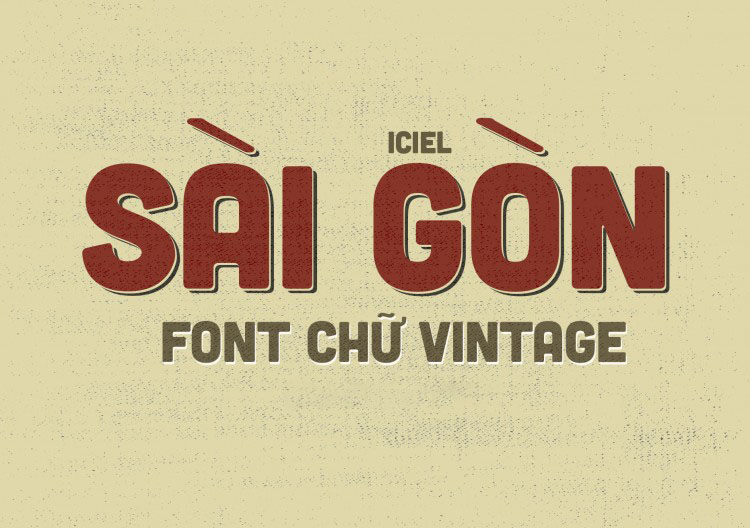
Font chữ béo (Extra Bold hoặc Black) là các kiểu chữ có độ dày nét lớn, mang lại hiệu ứng thị giác mạnh mẽ và khả năng thu hút sự chú ý ngay lập tức. Việc sở hữu bộ download font chữ béo giúp các nhà thiết kế và kiến trúc sư tạo ra những tiêu đề nổi bật cho hồ sơ dự án, bảng hiệu homestay hay các ấn phẩm truyền thông thương hiệu.
Đặc điểm nhận diện của dòng font chữ béo trong thiết kế đồ họa
Điểm lôi cuốn của các bộ phông chữ này chính là cấu trúc nét dày, vững chãi, tạo nên sự tin cậy và trọng lượng cho thông điệp. Khác với các kiểu chữ mảnh mai thanh thoát, font chữ béo tập trung vào việc chiếm lĩnh không gian hiển thị, giúp các từ khóa quan trọng trở nên tách bạch hoàn toàn với phần nội dung phụ. Các phiên bản Việt hóa được tinh chỉnh kỹ lưỡng giúp các dấu thanh (huyền, sắc, hỏi, ngã, nặng) không bị bết dính vào thân chữ, duy trì sự mạch lạc và tính thẩm mỹ ổn định cho văn bản.
Sự chuyên nghiệp của dòng font này còn thể hiện qua khả năng biểu cảm đa dạng. Những bộ font béo có đường bo tròn thường mang lại cảm giác thân thiện, vui vẻ, trong khi các kiểu font béo góc cạnh lại toát lên vẻ hiện đại và tư duy kiến trúc mạnh mẽ. Đây là phương án hiệu quả để định hình phong cách cho các công trình nhà lắp ghép, văn phòng container hoặc các không gian sống đòi hỏi cá tính riêng biệt và sự đột phá trong nhận diện.
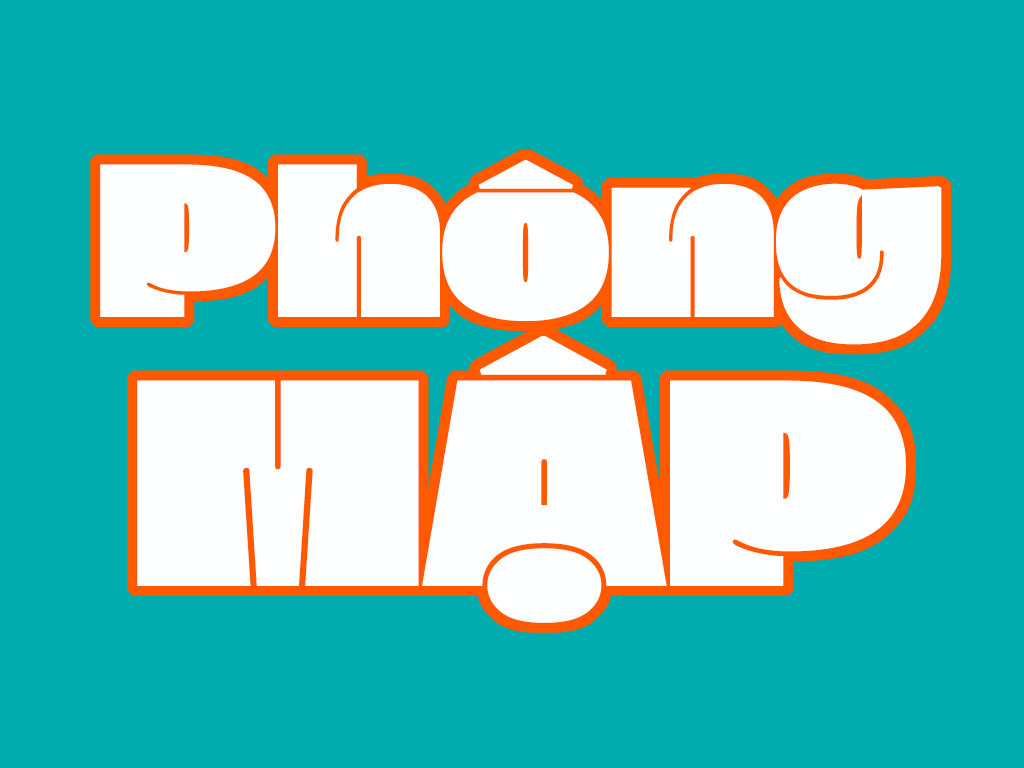
Thông tin kỹ thuật và tải font chữ béo Việt hóa trọn bộ
Để hỗ trợ bạn lựa chọn được kiểu chữ phù hợp với tính chất công việc, dưới đây là bảng thông số chi tiết của một số dòng phông chữ đậm nét phổ biến hiện nay.
| Dòng Font tiêu biểu | Đặc tính thiết kế | Ứng dụng phù hợp |
|---|---|---|
| SVN-Gilroy Black | Hình học tối giản, hiện đại, cực đậm | Logo, tiêu đề hồ sơ dự án |
| UTM Bebas | Nét cao, hẹp, độ dày ổn định | Biển cảnh báo, tiêu đề Poster |
| iCiel Cubano | Nét dày, bo góc mềm mại, thân thiện | Bảng tên Homestay, Cafe |
| Bango Font | Tròn trịa, vui nhộn, độ phủ lớn | Sự kiện trẻ em, trang trí decor |
Tư vấn trình bày: Khi sử dụng tải font chữ béo cho các bản vẽ kỹ thuật hoặc hồ sơ năng lực, bạn nên đặt chúng trên nền màu đơn sắc để tôn vinh sự vững chãi của bộ chữ. Việc phối hợp giữa một tiêu đề “béo” và một đoạn mô tả bằng font Sans-serif mảnh sẽ tạo ra sự phân cấp thông tin khoa học và dễ theo dõi.
03 Ứng dụng đưa phông chữ đậm nét vào thực tế kiến trúc
Nhờ diện mạo giàu sức hút và tính ứng dụng đa dạng, bộ phông chữ này mang lại giá trị thực tế lớn trong khâu quảng bá và hoàn thiện công trình:
- Hệ thống biển hiệu cho nhà lắp ghép: Những nét chữ dày rất ăn ý khi được gia công cắt laser trên các chất liệu alu hoặc gỗ. Font chữ này giúp biển chỉ dẫn hoặc tên khu nghỉ dưỡng toát lên vẻ chỉn chu và dễ nhận diện từ khoảng cách xa.
- Thiết kế Poster và Profile doanh nghiệp: Sử dụng font chữ béo cho các số liệu về công suất nhà xưởng hoặc diện tích văn phòng container giúp thông tin trở nên nổi bật, tạo sự tin tưởng về quy mô dự án đối với khách hàng.
- Trang trí không gian nội thất hiện đại: Bạn có thể dùng font béo để in decal dán tường hoặc làm tranh quotes tại sảnh chờ, tạo điểm nhấn đầy thẩm mỹ và khơi gợi cảm hứng sáng tạo cho người sử dụng không gian.
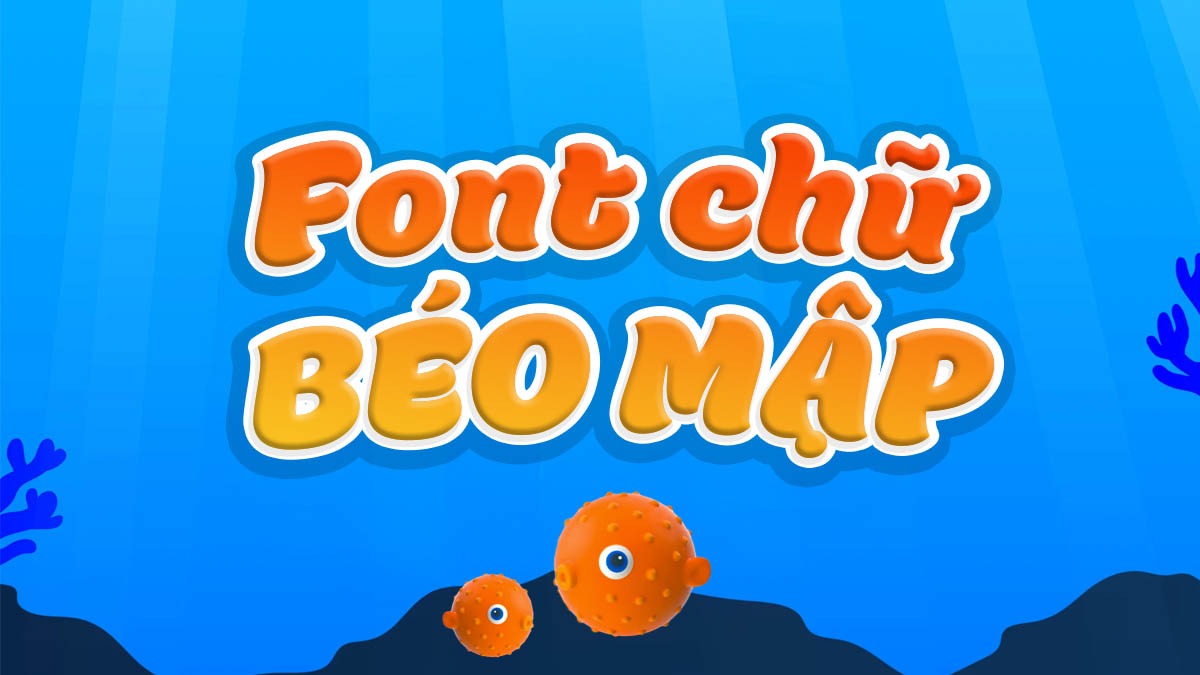
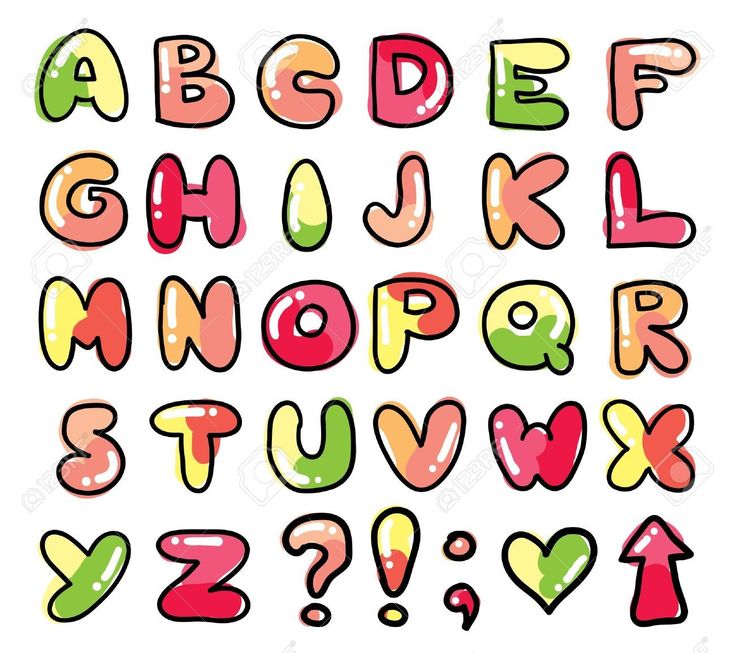
03 Lưu ý để bố cục font chữ béo hài hòa và không gây mỏi mắt
Để khai thác hiệu quả vẻ đẹp của dòng font đặc thù này mà không làm giảm tính chuyên nghiệp của bản thiết kế, người dùng nên lưu tâm một số lưu ý sau:
- Kiểm soát mật độ văn bản: Chỉ nên sử dụng font chữ béo cho tiêu đề hoặc các cụm từ ngắn. Việc lạm dụng cho các đoạn văn bản dài sẽ khiến trang giấy trở nên nặng nề, bí bách và gây khó khăn lớn cho việc tiếp nhận thông tin.
- Nới rộng khoảng cách chữ: Với các phông chữ có độ đậm cao, các ký tự thường trông rất sát nhau. Bạn nên nới rộng khoảng cách giữa các chữ cái một chút để văn bản thông thoáng và rõ nét hơn khi in ấn.
- Lựa chọn độ tương phản phù hợp: Font chữ béo phát huy hiệu quả thị giác cao khi phối các tông màu có độ tương phản rõ rệt (như chữ trắng trên nền tối hoặc ngược lại), giúp các đường nét vuông vức hoặc bo tròn được tôn vinh rõ ràng.